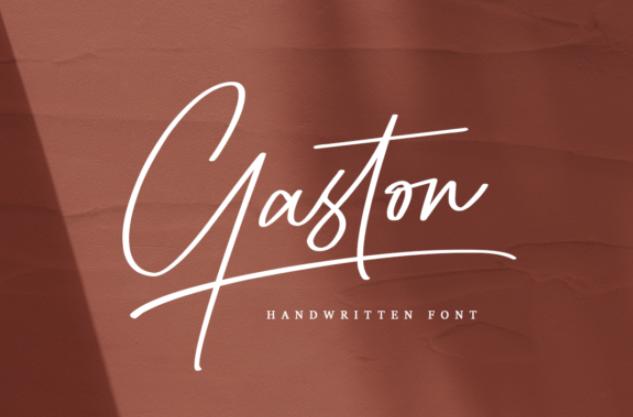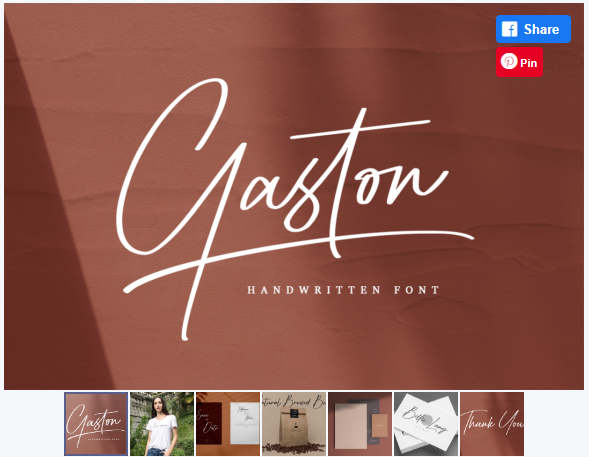
[Creativefabrica] Gaston Font (Moove Studio)
Gaston - стильный скриптовый шрифт. Он придаст изюминку любому дизайнерскому проекту, который вы желаете создать! Этот шрифт имеет кодировку PUA, что означает, что вы можете легко получить доступ ко всем удивительным глифам и лигатурам!